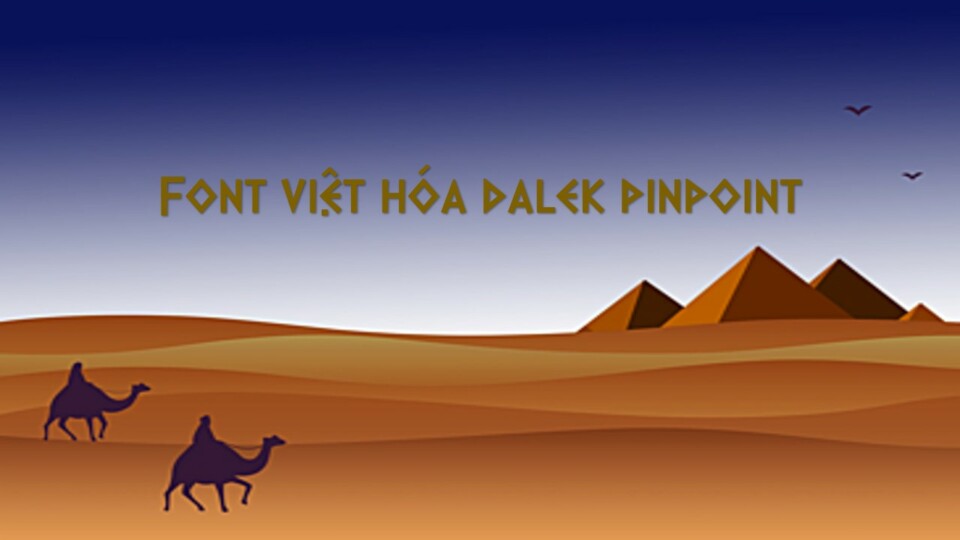
Giới thiệu về Font việt hóa Dalek PinPoint
Trong thế giới đồ họa, việc lựa chọn một Font Chữ phù hợp đóng vai trò quyết định đến tính thẩm mỹ của sản phẩm. Font việt hóa Dalek PinPoint là một cái tên nổi bật, mang phong cách mạnh mẽ và cá tính. Đây là phiên bản được tinh chỉnh kỹ lưỡng nhằm hỗ trợ đầy đủ các dấu tiếng Việt, giúp người dùng dễ dàng ứng dụng vào các dự án thiết kế mà không lo lỗi hiển thị. Với đường nét sắc sảo, bộ font này đặc biệt phù hợp cho những ai yêu thích sự phá cách và hiện đại trong trình bày văn bản.
Đặc điểm nổi bật của Font việt hóa Dalek PinPoint
Bộ phông chữ này sở hữu cấu trúc chữ cái độc đáo, lấy cảm hứng từ các ký tự cơ khí và phong cách khoa học viễn tưởng. Khoảng cách giữa các chữ cái được tối ưu hóa, tạo nên sự cân đối và dễ đọc ngay cả ở kích thước nhỏ. Font việt hóa Dalek PinPoint cung cấp nhiều định dạng khác nhau, cho phép nhà thiết kế linh hoạt trong việc tạo tiêu đề sách, poster phim hoặc các ấn phẩm quảng cáo đòi hỏi sự khác biệt. Đặc biệt, các ký tự đặc biệt và hệ thống dấu thanh được chăm chút tỉ mỉ, đảm bảo giữ nguyên tinh thần nguyên bản của thiết kế Dalek PinPoint.
Kết luận về bộ phông chữ độc đáo